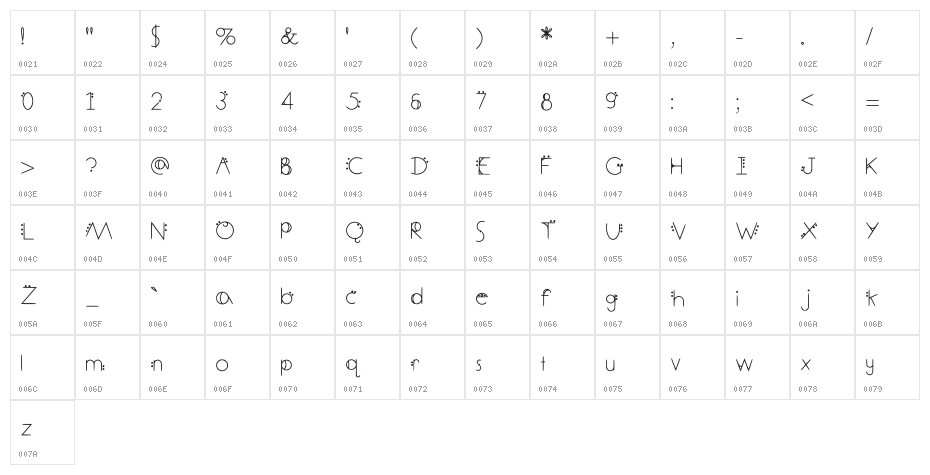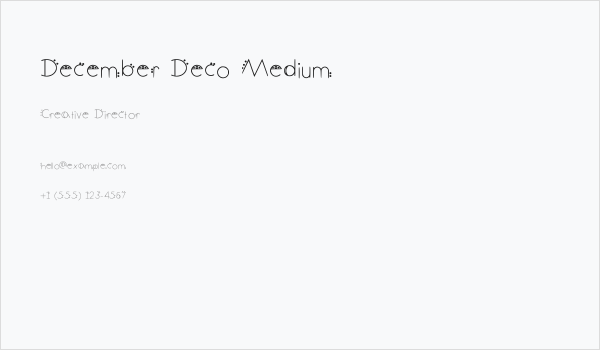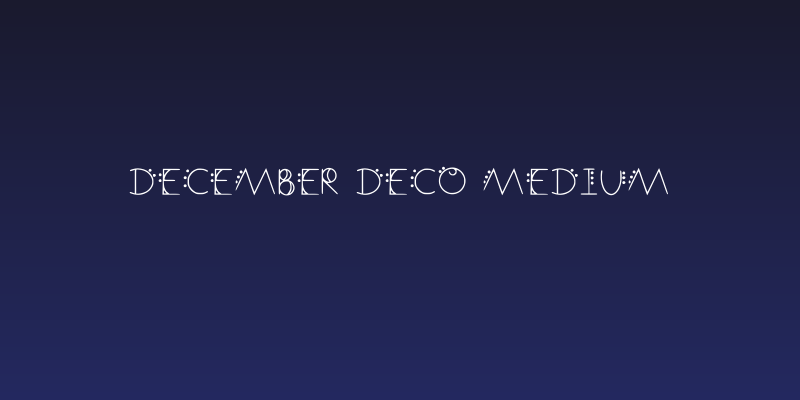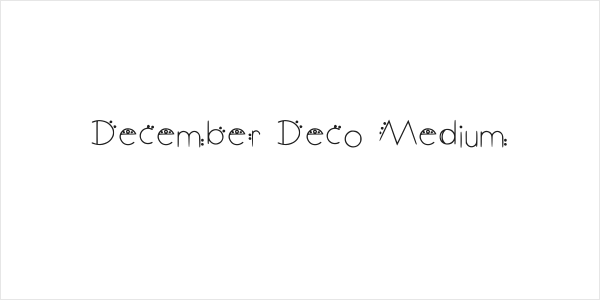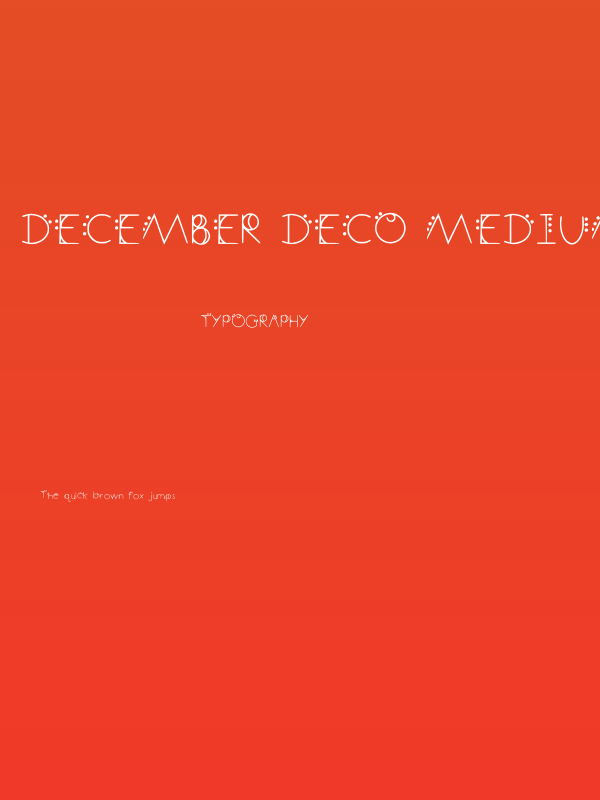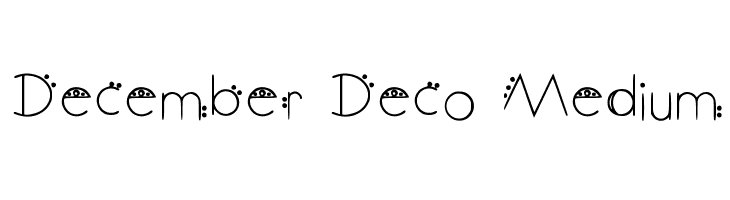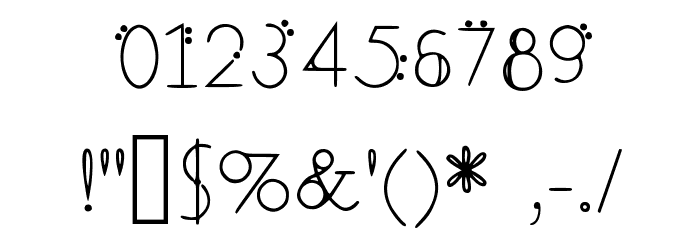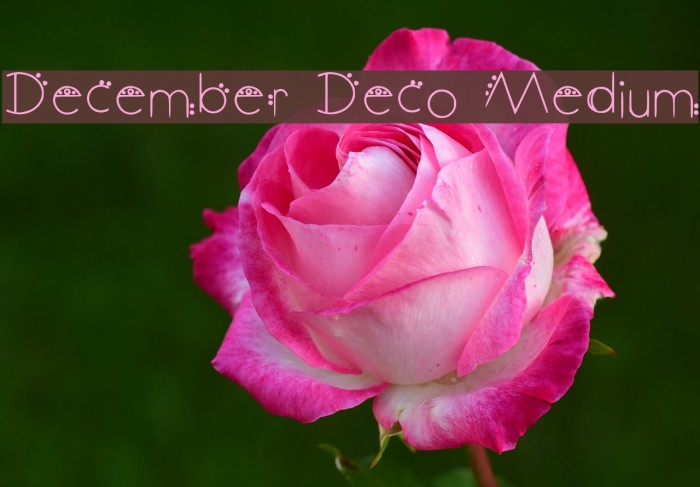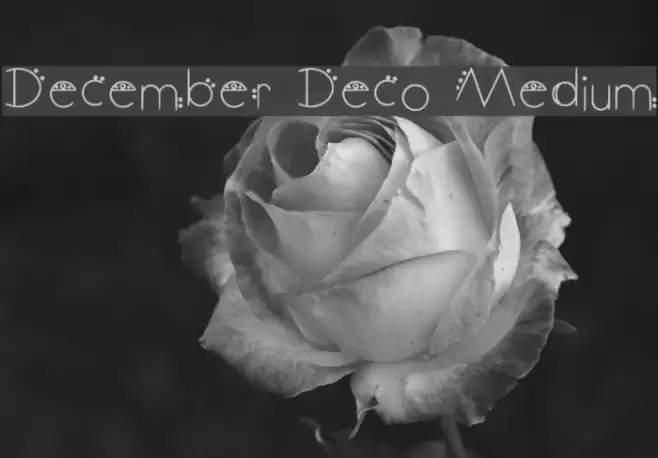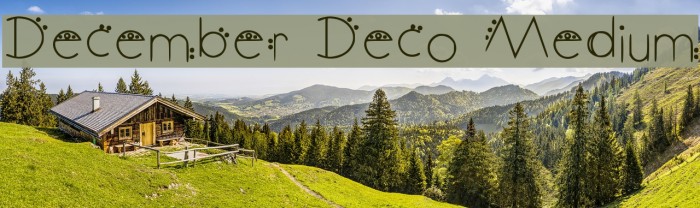
December Deco Medium Font
| Caso de uso | Headlines, Logos, Artistic projects |
| Projetos propostos | Ideal for creative projects such as event invitations, artistic posters, branding for unique products, and any design requiring a playful and decorative touch. |